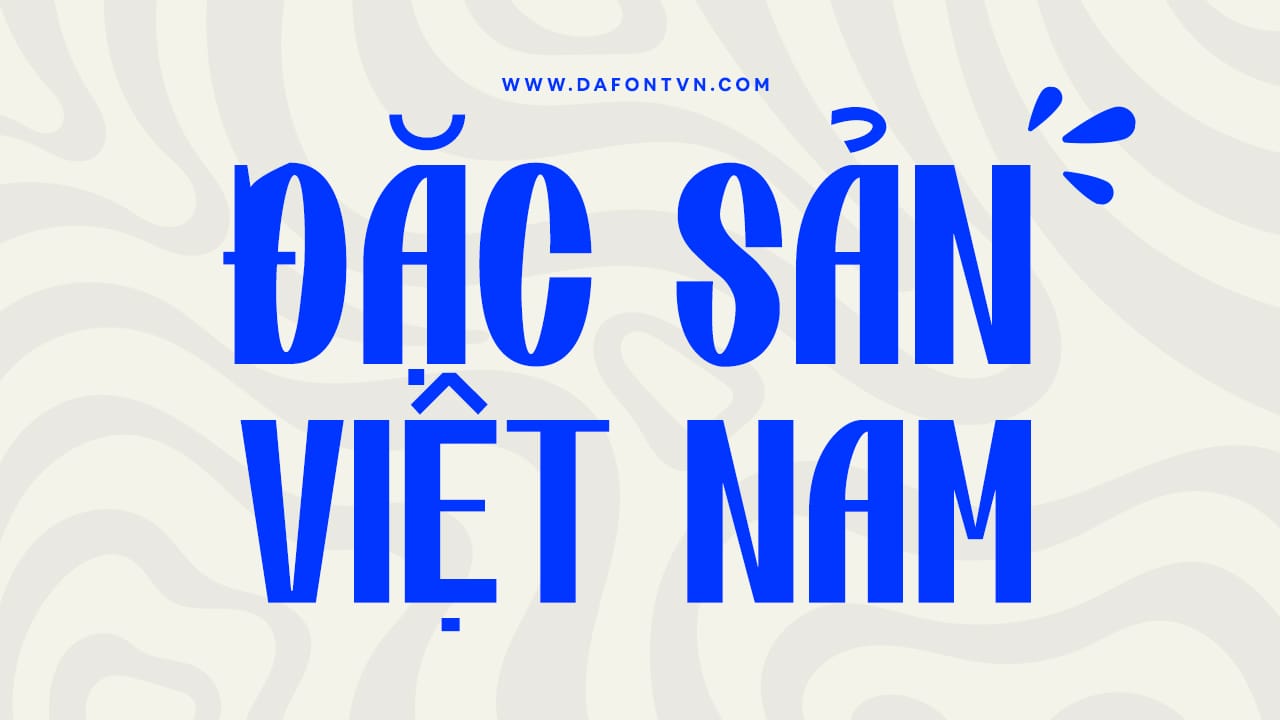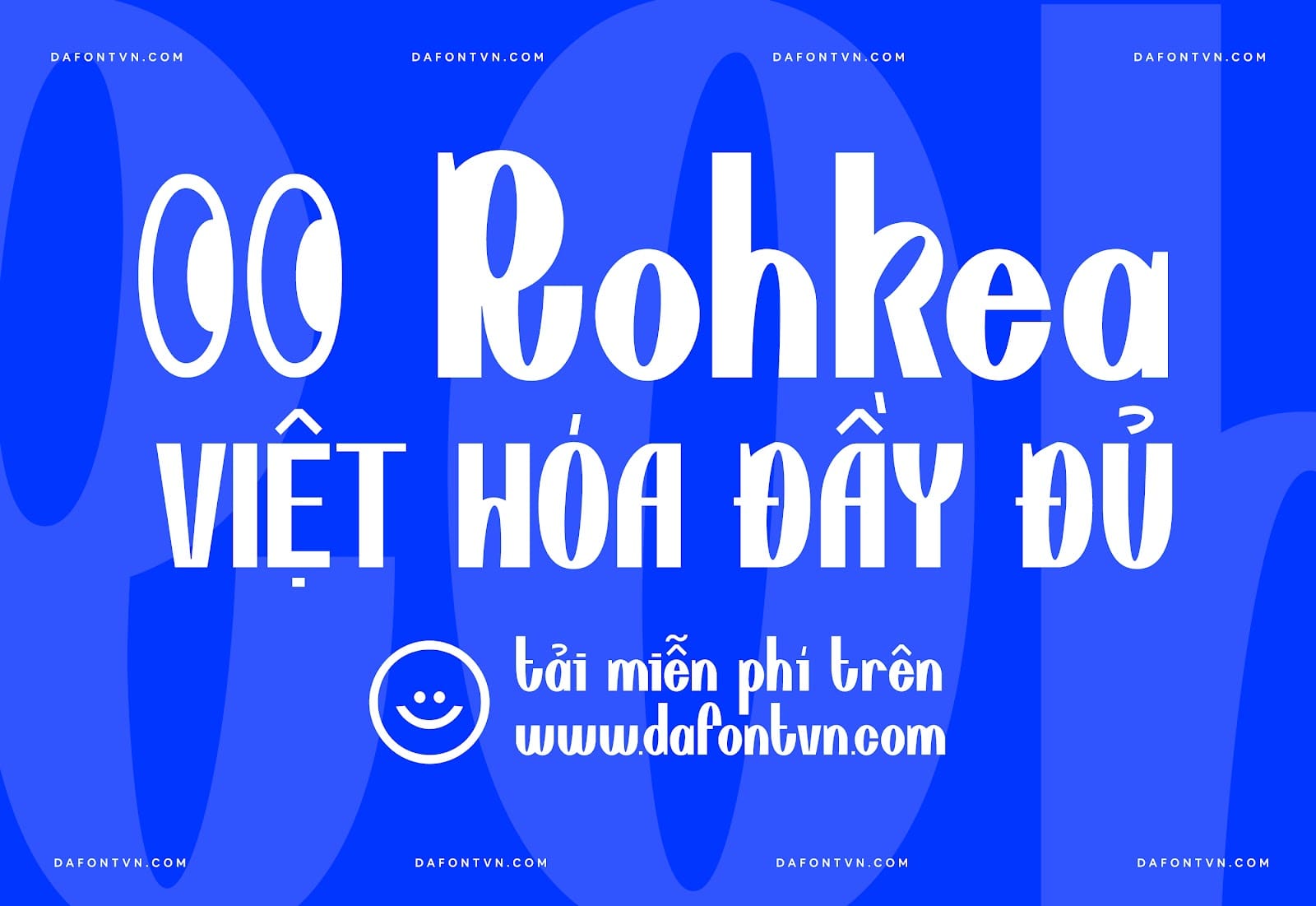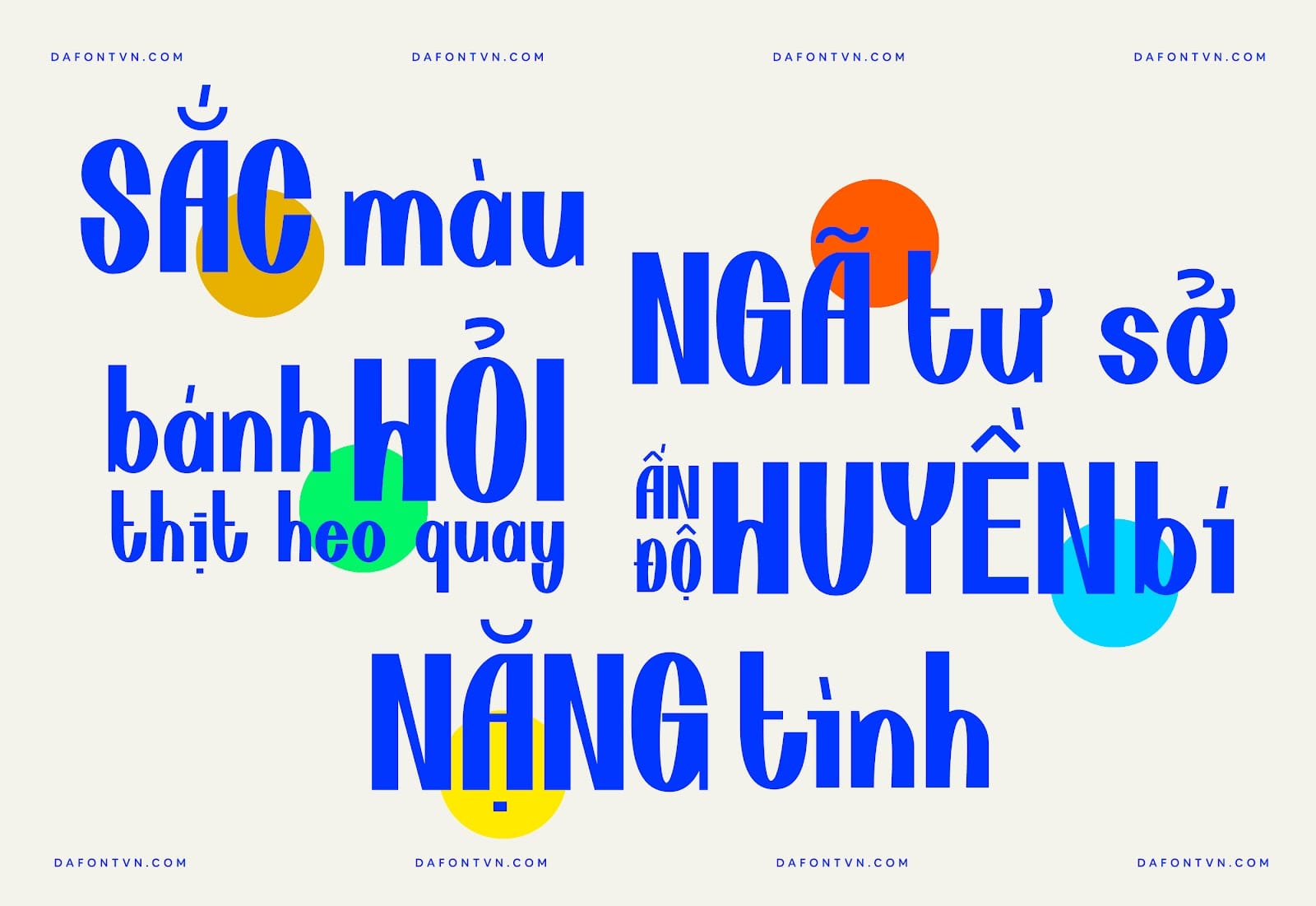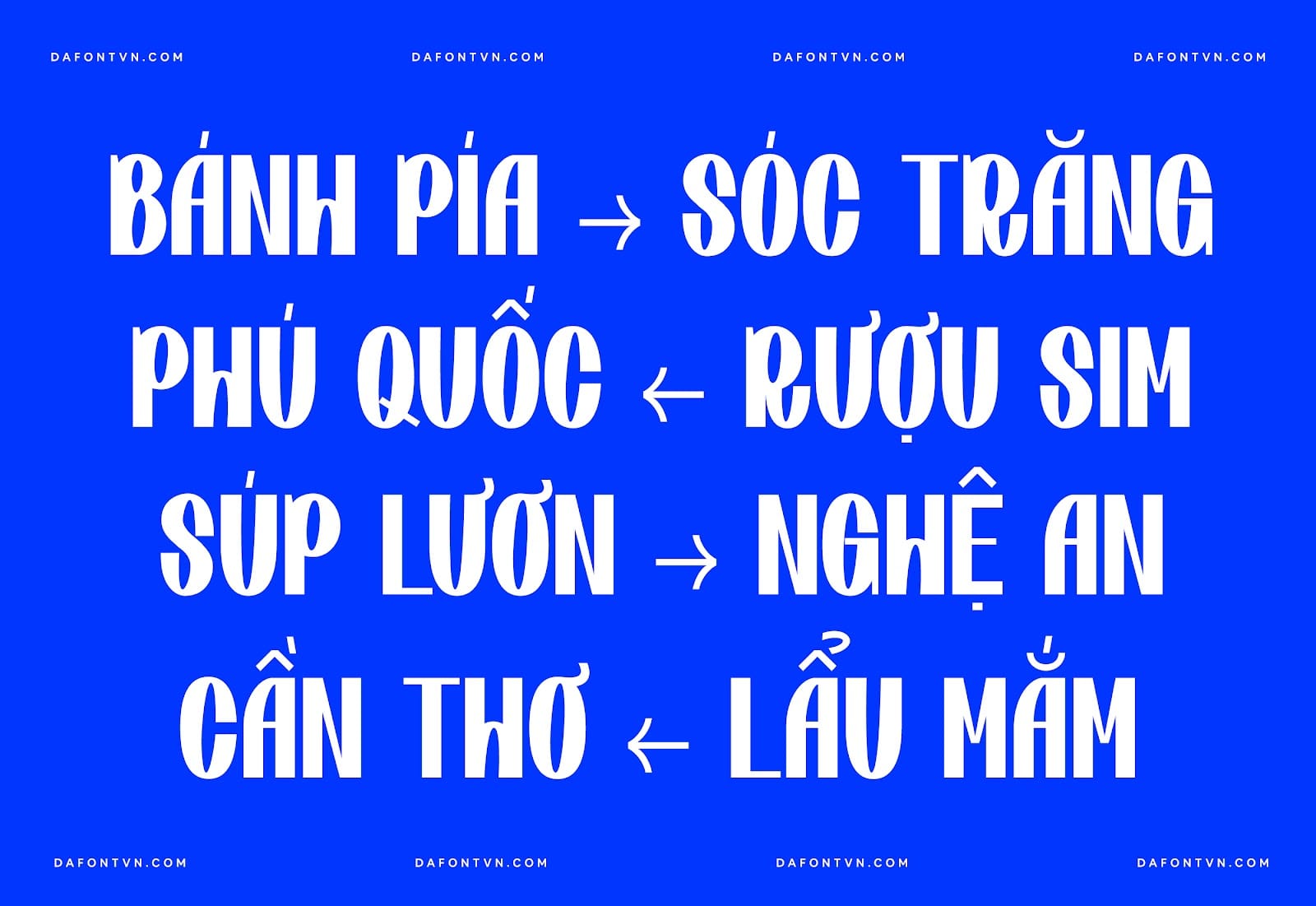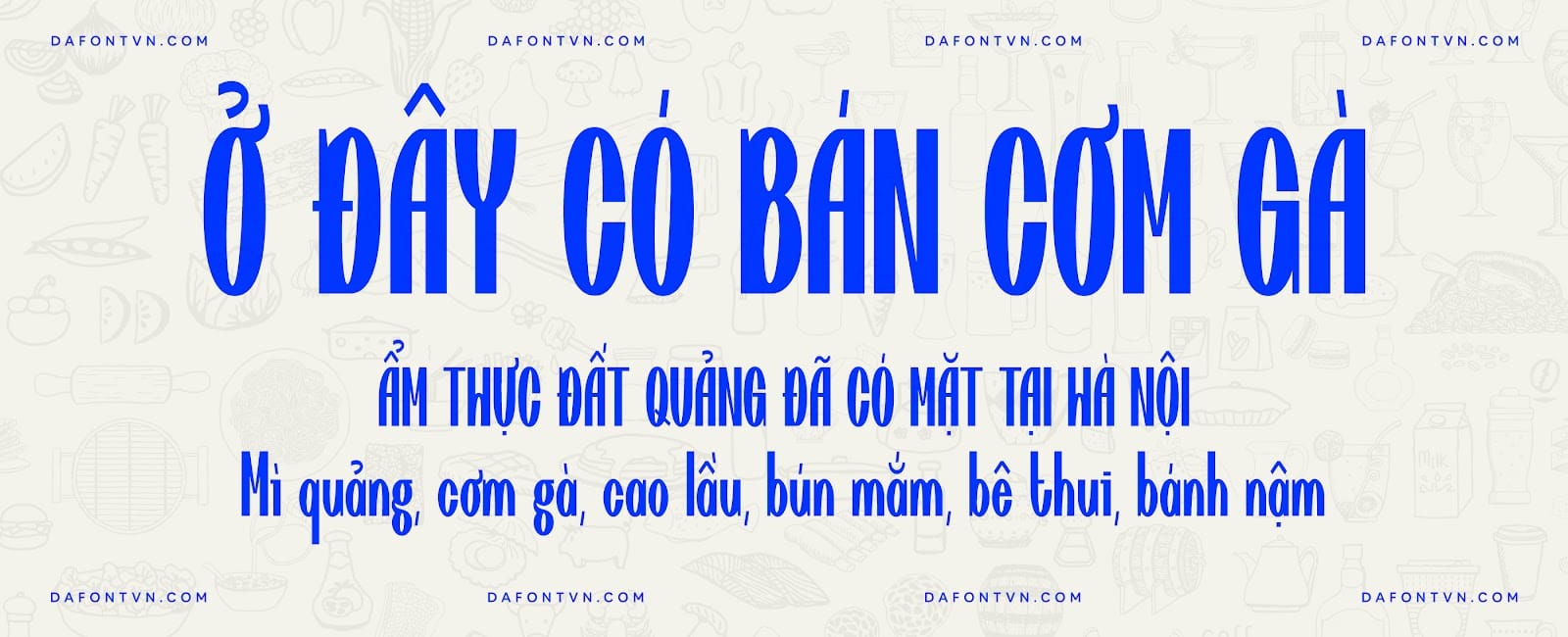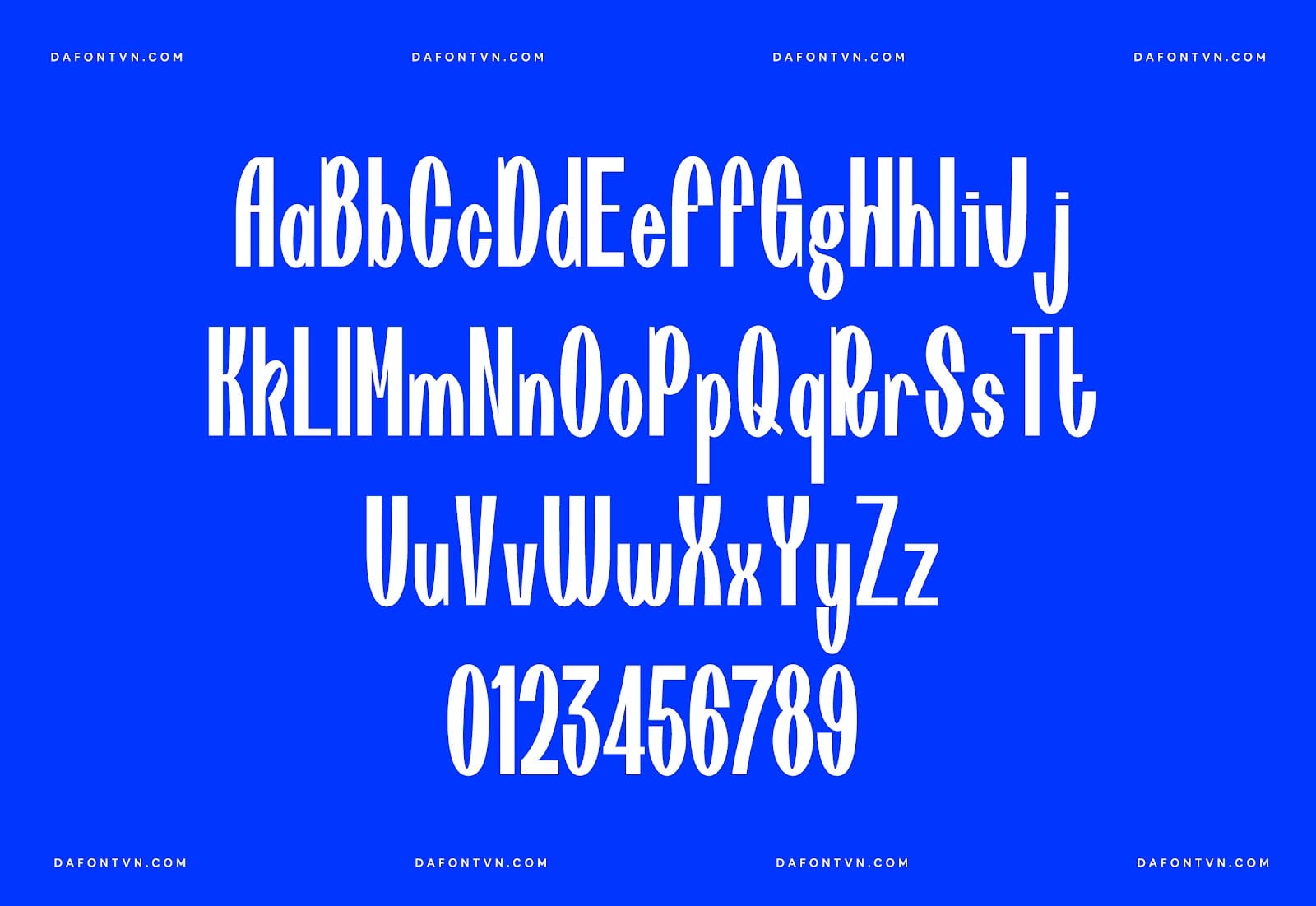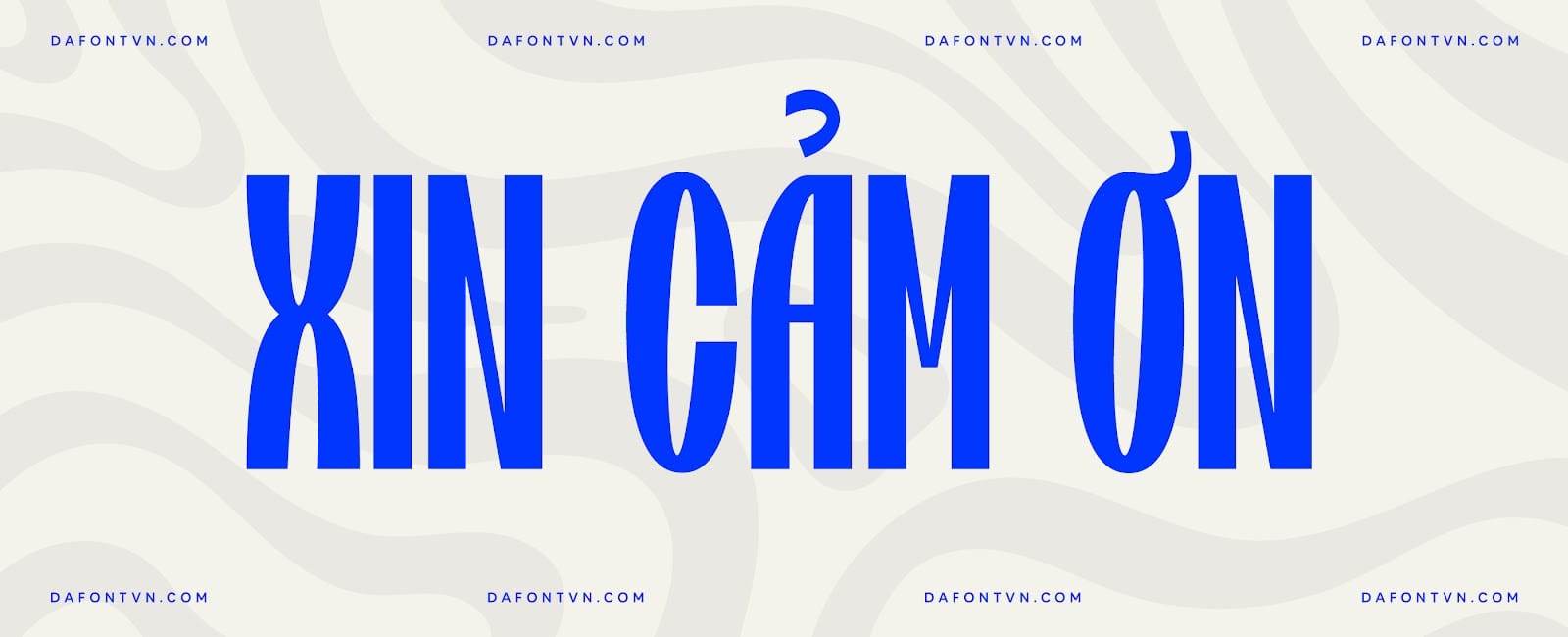
Font SK Rohkea Việt hóa – Font hiển thị đẹp mắt
SK Rohkea là một kiểu chữ hiển thị rất đẹp mắt. Các đặc điểm chính của kiểu chữ là độ nghiêng không đổi của hình bầu dục và sự kéo dài của các hình dạng. Chúng mang đến cho kiểu chữ một cái nhìn độc đáo, đặc biệt khi nó được sử dụng trong các tiêu đề.
Nhờ sự kết hợp giữa hiện đại và tinh xảo, kiểu chữ này rất phù hợp cho một loạt các nhiệm vụ thiết kế rộng lớn, cho dù đó là in ấn hay thiết kế web. Nó phù hợp để sử dụng làm tiêu đề cho nhiều thiết kế khác nhau như tạp chí, bìa sách, quảng cáo, poster, sản phẩm…
Font được việt hóa đầy đủ, kerning, chỉnh sửa lại 1 số dấu cho phù hợp hơn cũng như được tối ưu lại để sử dụng dễ dàng trên bất kỳ phần mềm nào.